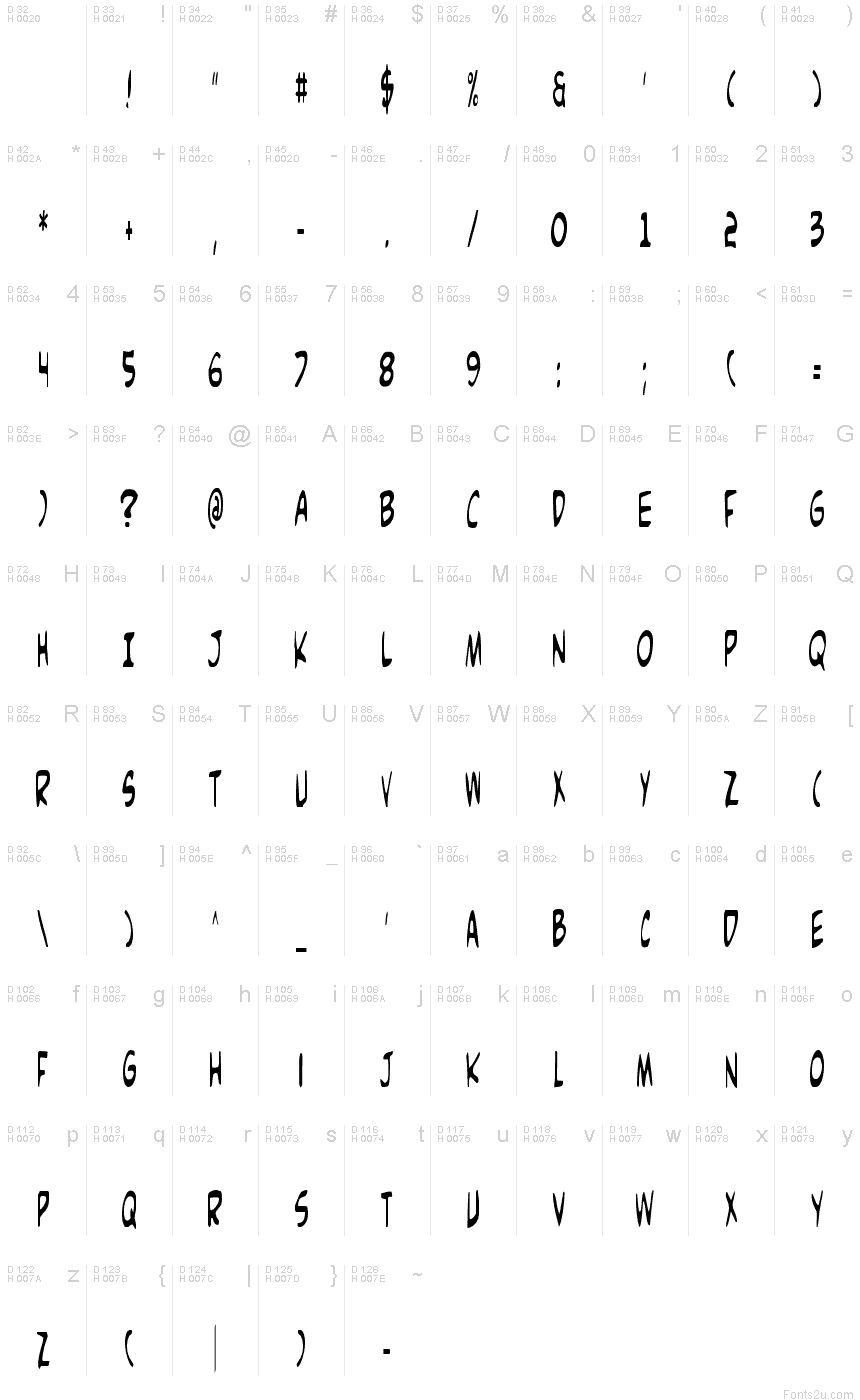
Comic Book Commando Condensed
Comic Book Commando Condensed od Iconian Fonts to darmowy, komiksowy krój displayowy, który uderza z siłą pieczątki. Wysokie, wąskie litery o skocznym, ręcznie rysowanym rytmie sprawiają wrażenie wyjętych prosto z komiksowego kadru – głośne, szybkie i nieco zadziorne, a przy tym czytelne.
Dzięki Comic Book Commando Condensed Twoje słowa wyskoczą z okładek komiksów, dymków, napisów akcji, plakatów w stylu retro, paczek naklejek, miniatur na YouTube czy ekranów gier arcade. Zadbaj o nieco większy światłoznak (tracking), aby litery mogły „odetchnąć” w mniejszym rozmiarze i połącz ten darmowy font z czystym bezszeryfowym krojem w tekście głównym, aby utrzymać wyraziste nagłówki w ryzach.